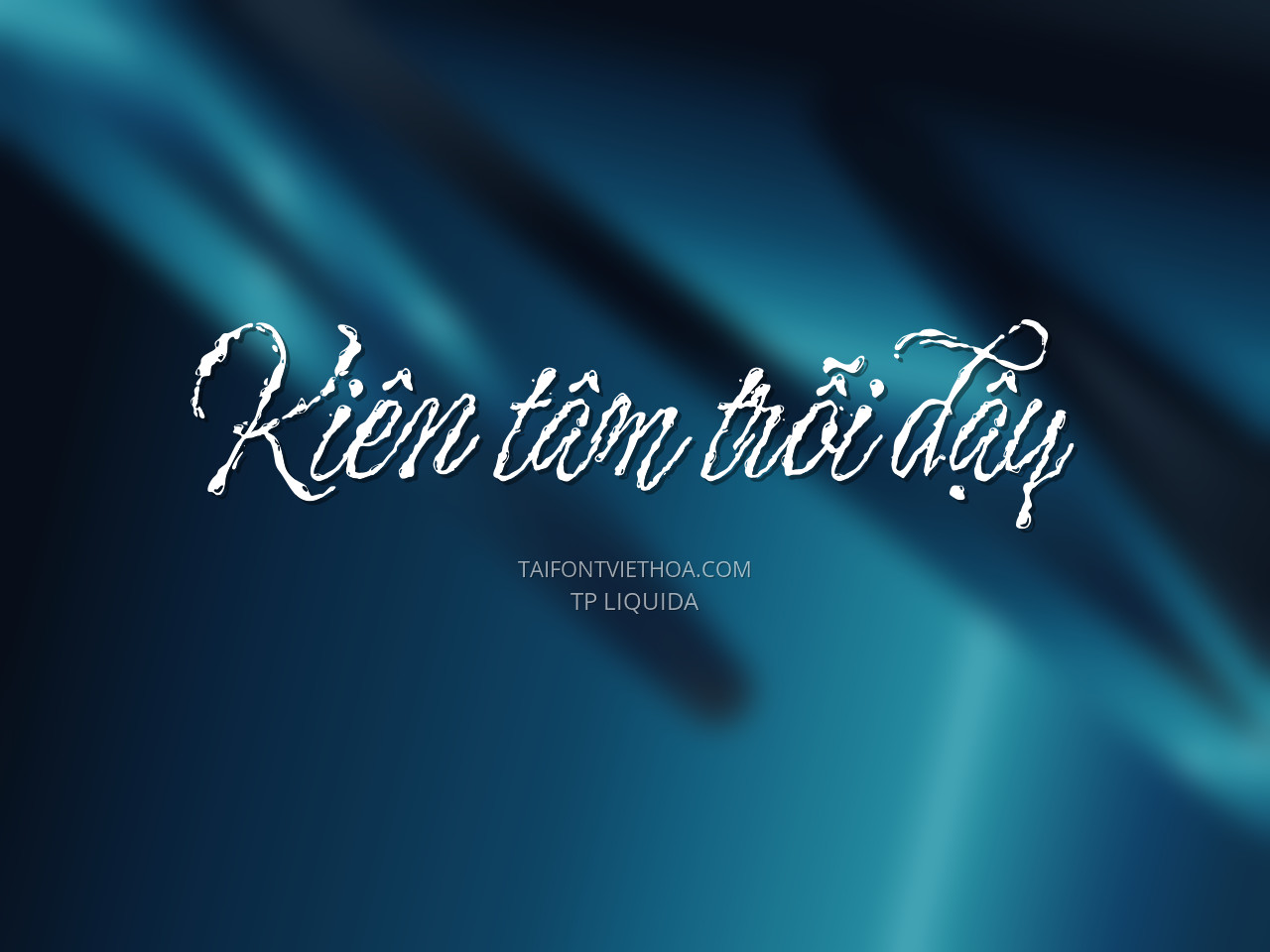
Giới thiệu về font TP Liquida – Kiểu chữ script mềm mại, thanh lịch và bay bổng
TP Liquida là phiên bản Việt hóa của font Liquida – một kiểu chữ script mang phong cách mềm mại, thanh lịch và rất bay bổng. Font được thiết kế với các nét chữ uyển chuyển, nhẹ nhàng và tinh tế, tạo cảm giác tự nhiên và gần gũi, rất phù hợp cho các dự án thiết kế thiệp cưới, thiệp mời, bao bì mỹ phẩm và các sản phẩm sáng tạo cá nhân.
Phiên bản Việt hóa của TP Liquida đã được Taifontviethoa.comchăm sóc kỹ lưỡng, hỗ trợ đầy đủ dấu tiếng Việt cùng hơn 60 ngôn ngữ khác. Font giúp các nhà thiết kế dễ dàng áp dụng trong nhiều dự án sáng tạo với phong cách nhẹ nhàng, thanh lịch và duyên dáng.
Thiết kế script bay bổng – Lý tưởng cho thiệp cưới và thương hiệu mỹ phẩm
TP Liquida sở hữu các nét chữ mềm mại, liền mạch với độ nghiêng nhẹ nhàng và các ligature tinh tế, tạo nên sự hài hòa và bay bổng trong tổng thể thiết kế. Font mang lại cảm giác nữ tính, duyên dáng và rất phù hợp cho tiêu đề, logo, bao bì hoặc các phần thiết kế cần điểm nhấn mềm mại và thanh lịch.
Ứng dụng lý tưởng: thiệp cưới, thiệp mời, logo thương hiệu mỹ phẩm, bao bì sản phẩm cao cấp, bìa sách nghệ thuật, poster sự kiện và các dự án sáng tạo cần phong cách nhẹ nhàng, duyên dáng. Ngành nghề phù hợp: cưới hỏi, mỹ phẩm, thời trang, nghệ thuật, truyền thông sáng tạo và các thương hiệu định vị theo phong cách nữ tính, thanh lịch.